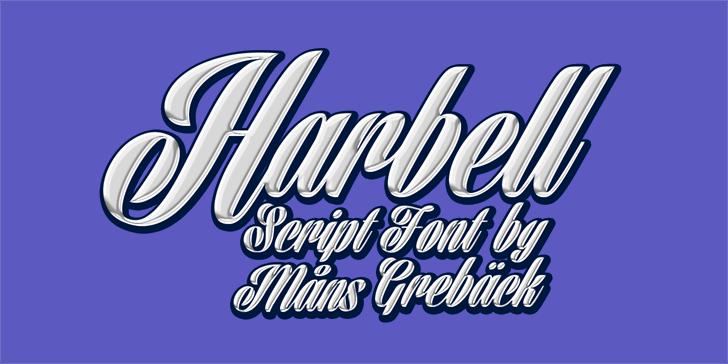
A Harbell font é uma escolha perfeita para quem procura uma fonte de exibição vibrante e moderna que combina eficácia visual com estilo único. Criada por Måns Grebäck em 2013, esta fonte personalizada permite uma experiência impecável no campo da design gráfico. Seu design clean e atemporal é ideal para aplicar texturas e ambientes diversos, seja em logos, títulos de página ou qualquer outro ponto de atenção na sua marca. A Harbell apresenta linhas definidas que se movem harmoniosamente, proporcionando um texto alegre e envolvente. Suas características distintivas incluem uma proporção equilibrada e uma tipografia fluida, garantindo que o texto seja fácil de ler em qualquer dispositivo. Este é um recurso gráfico perfeito para quem busca expressar sua marca de maneira única, combinando sofisticação com estilo moderno.